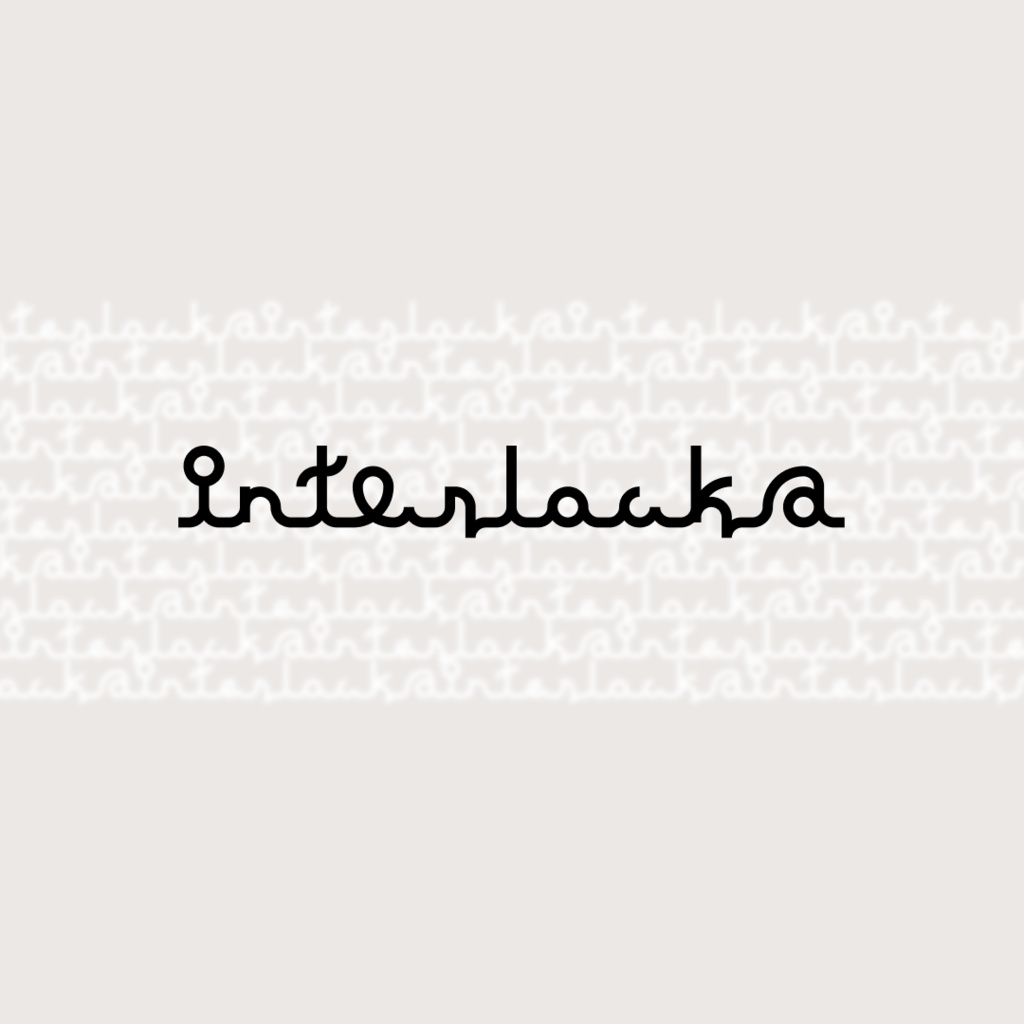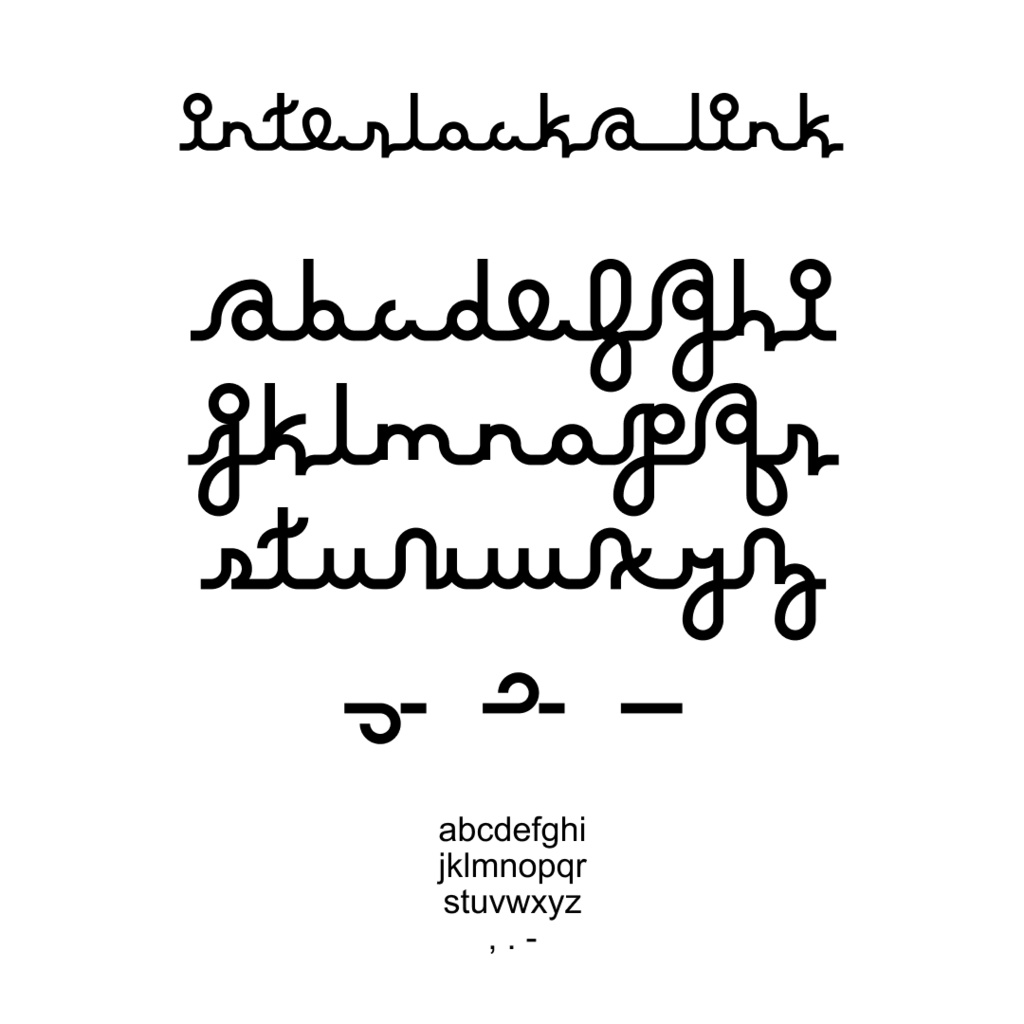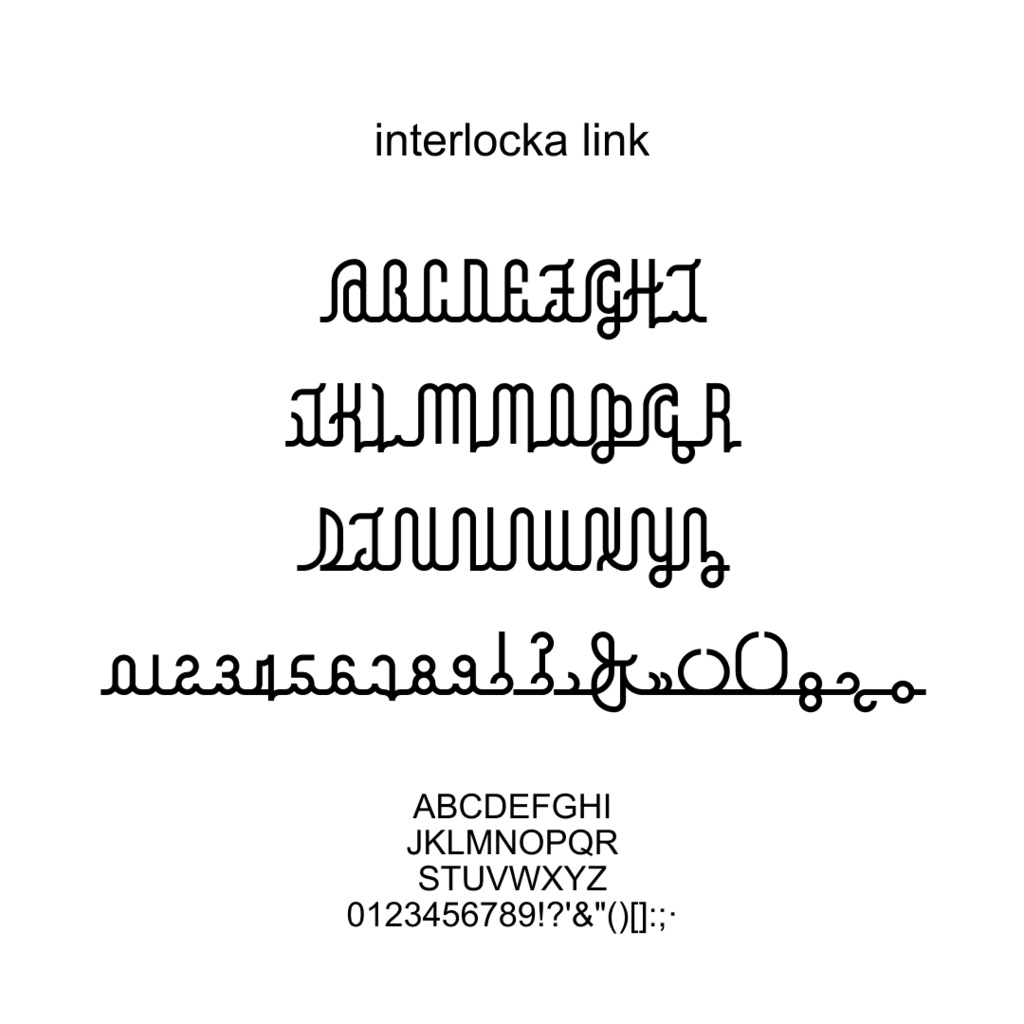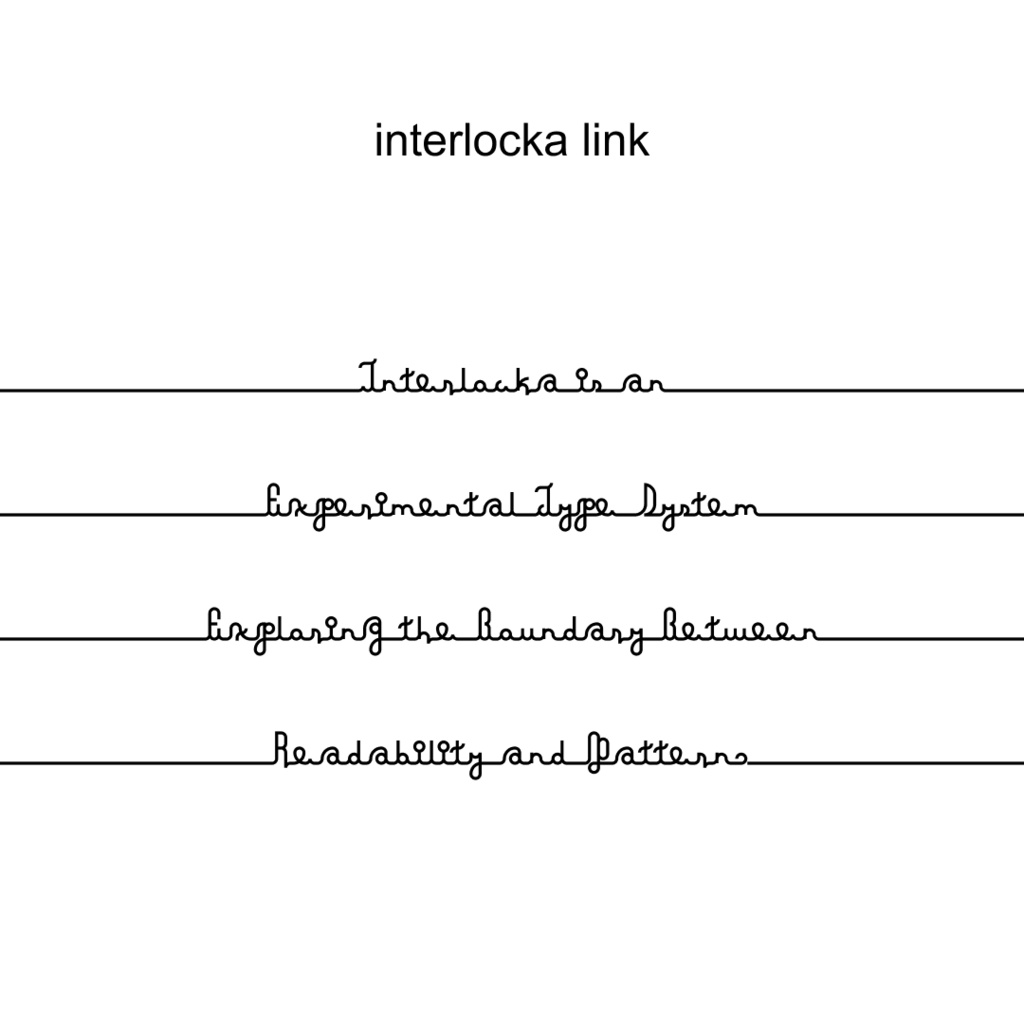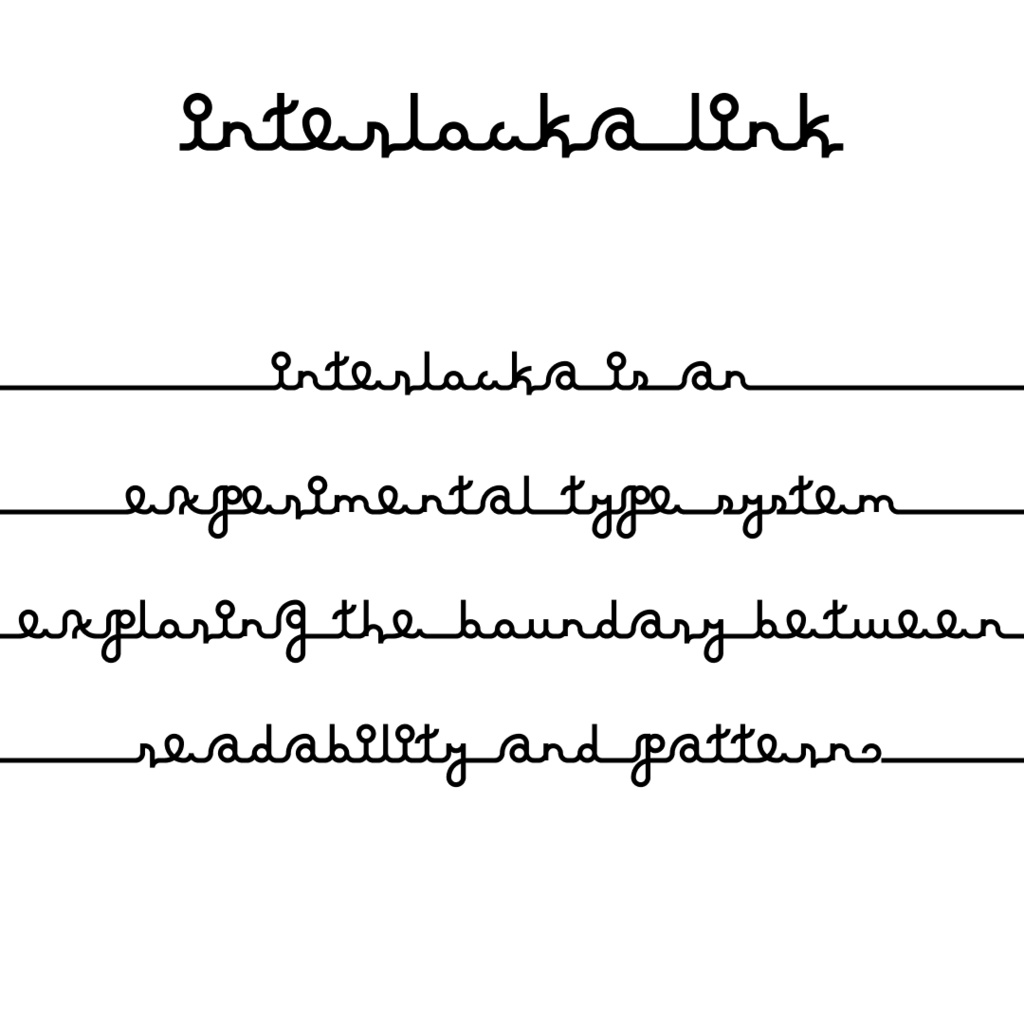
interlocka【商用利用可】実験的ディスプレイフォント
interlocka は、「読める」と「模様」の境界を探りながら制作している、継続的に拡張される実験的なタイプシステムです。 2種類の曲線と直線だけを用い、文字同士が一続きの流れとして繋がるように構成されています。 文字列の連続性を保つため、単語間にはスペースではなくハイフン(-)の使用を推奨しています。 完全な可読性よりも、空気感・構造・視覚的な心地よさを重視しています。 interlocka は単体フォントではなく、段階的に拡張されていくタイプシステムとして設計されています。 現在も継続的に制作・調整を行っており、シリーズ追加・ウェイト追加・記号拡張などを通して、体系全体を発展させていく予定です。 購入者は、購入時点以降のアップデートを追加料金なしで受け取れます。 ※ディスプレイ・デザイン用途向け ※実験的な性質上、一般的な文字組には適さない場合があります ◆フォントの仕様 ファイル形式:OpenType Font(.otf) ◆収録内容(2026/06/18現在) ■ interlocka link v1.1 Readability:7/10 (Interpretive) 対応文字:小文字アルファベット(a-z)、一部記号(, . -) ◆アップデート履歴 〇2026/5/15 interlocka link v1.0 公開 〇2026/6/18 interlocka link v1.1 公開 - OTF向けにアウトラインを再調整、曲線品質改善 〇2026/7/18 interlocka link v2.0 公開 - link の対応文字の大幅追加(英語大文字、数字、記号! ? ( ) [ ] · : ; & " ') ◆今後のアップデート予定 ・対応文字の追加 ・合字(リガチャー)の追加 ・スタイルバリエーションの追加 ※アップデート内容を保証するものではありません ※開発の進行に応じて価格改定を行う場合があります ◆利用規約 https://quiet-surface.booth.pm/items/8355991 ◆動作環境 OpenTypeフォントが利用可能な環境 ────────── Interlocka is an ongoing experimental type system exploring the boundary between readability and pattern. Built using only two types of curves and straight lines, characters are designed to flow continuously into one another. Rather than prioritizing perfect legibility, the system focuses on atmosphere, structure, and visual continuity. Interlocka is developed as an evolving type system, with future expansions including new series, weights, ligatures, and symbol sets. Purchasers receive all updates released after purchase at no additional cost.